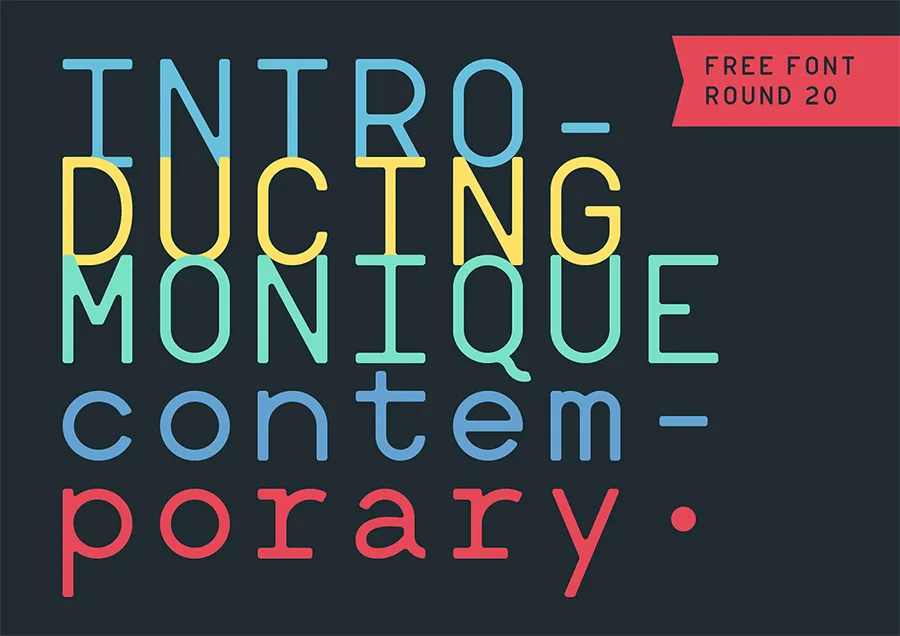
Monique Contemporary Font
A Monique Contemporary é uma fonte Mono criada pela Hederae Creative Shop. Suas linhas finas e bem definidas fazem dela uma escolha ideal para ambientes profissionais, como editoriais ou apresentações de trabalho. Esta fonte segue um layout rígido e modular que remete à contemporaneidade, incorporando influências modernas enquanto mantém sua essência funcional e clara. Perfeita tanto para textos detalhados quanto para cabeçalhos chamativos, a Monique Contemporary se destaca como uma escolha versátil. Suas linhas precisas garantem um layout impecável em páginas de revistas ou editoriais, enquanto sua simplicidade e modularidade permitem que ela seja usada tanto nas tabelas quanto nos parágrafos de texto. A Monique Contemporary é perfeita para qualquer projeto que exige uma fonte moderna e profissional, sem deixar de lado seu carácter claramente contemporâneo.